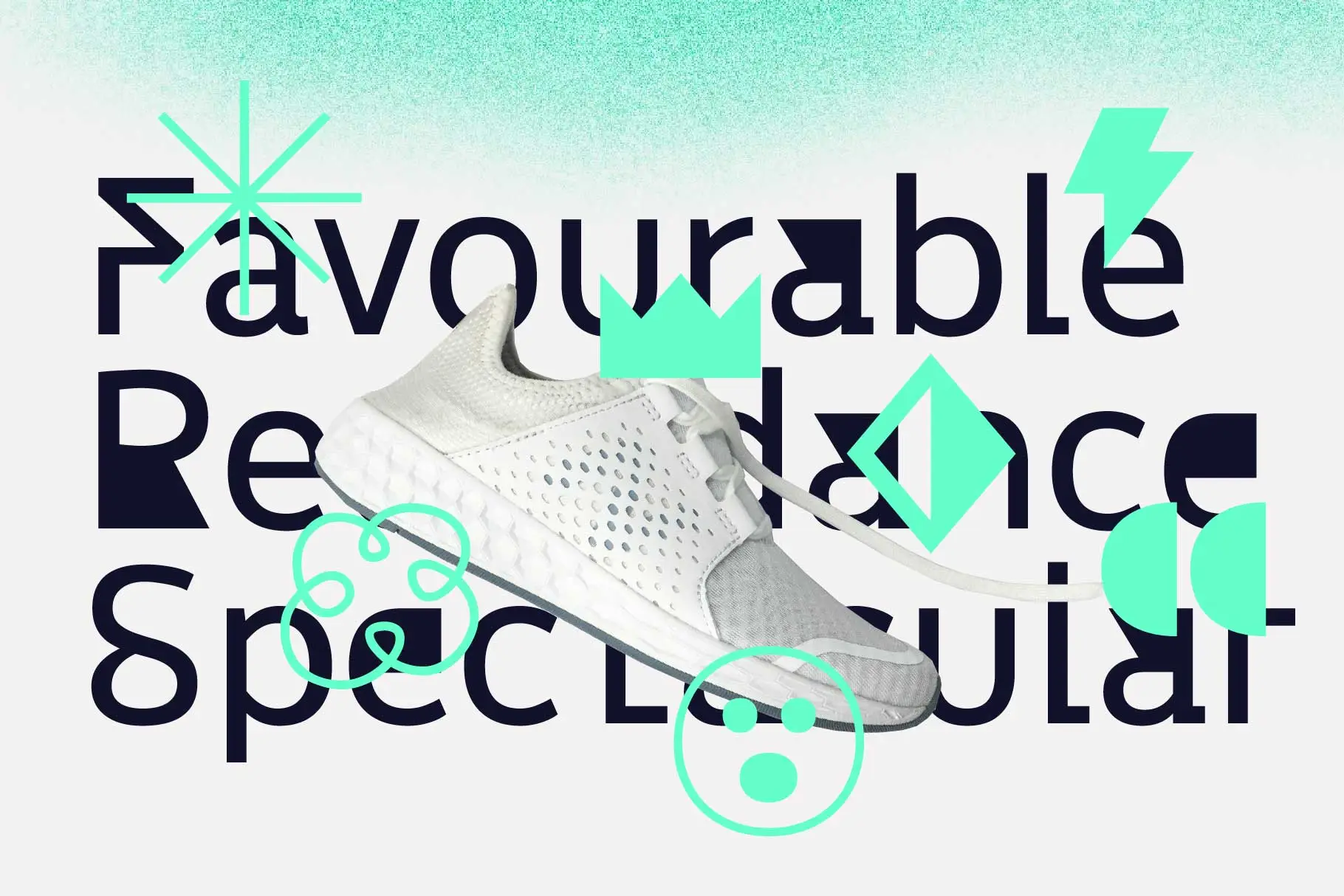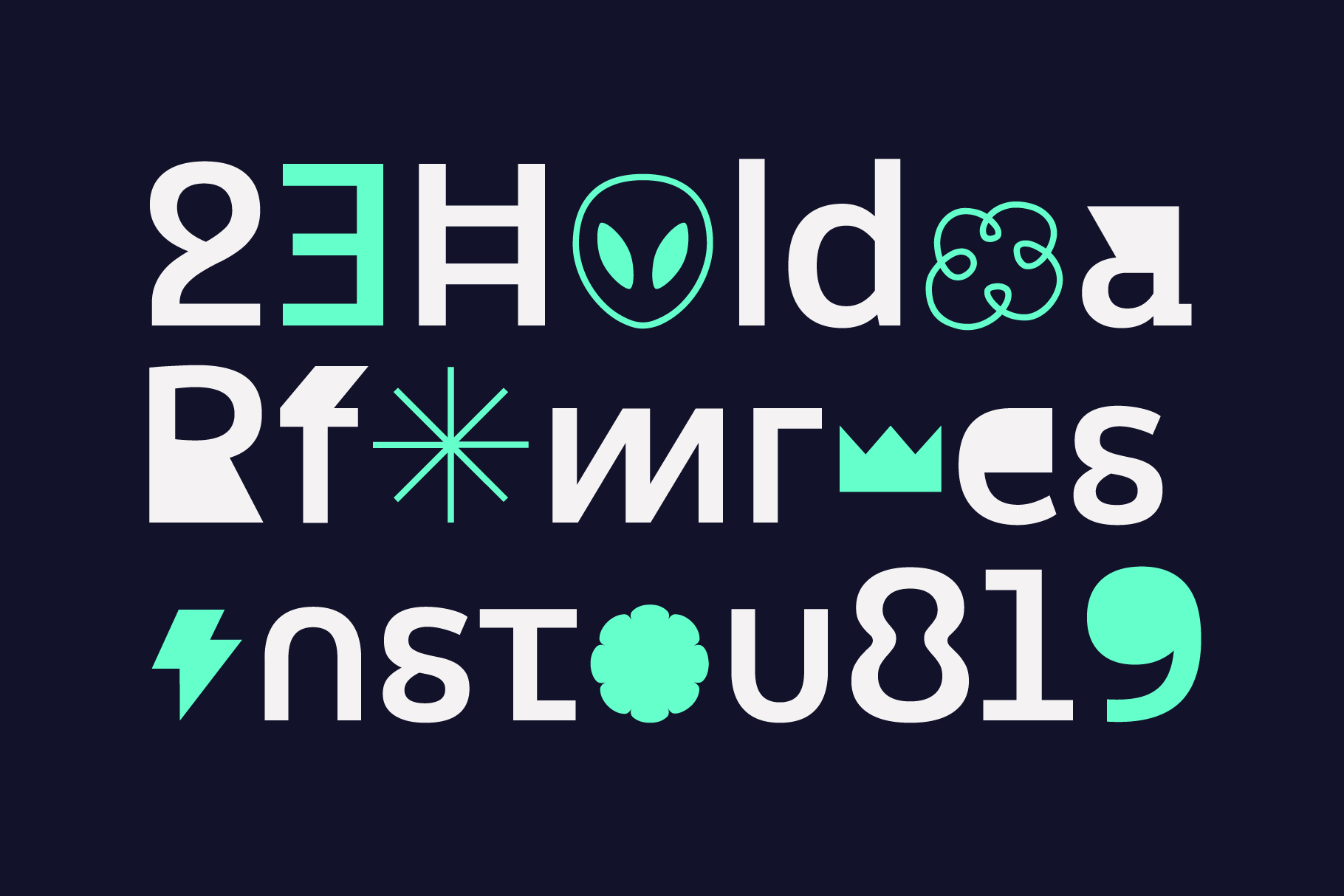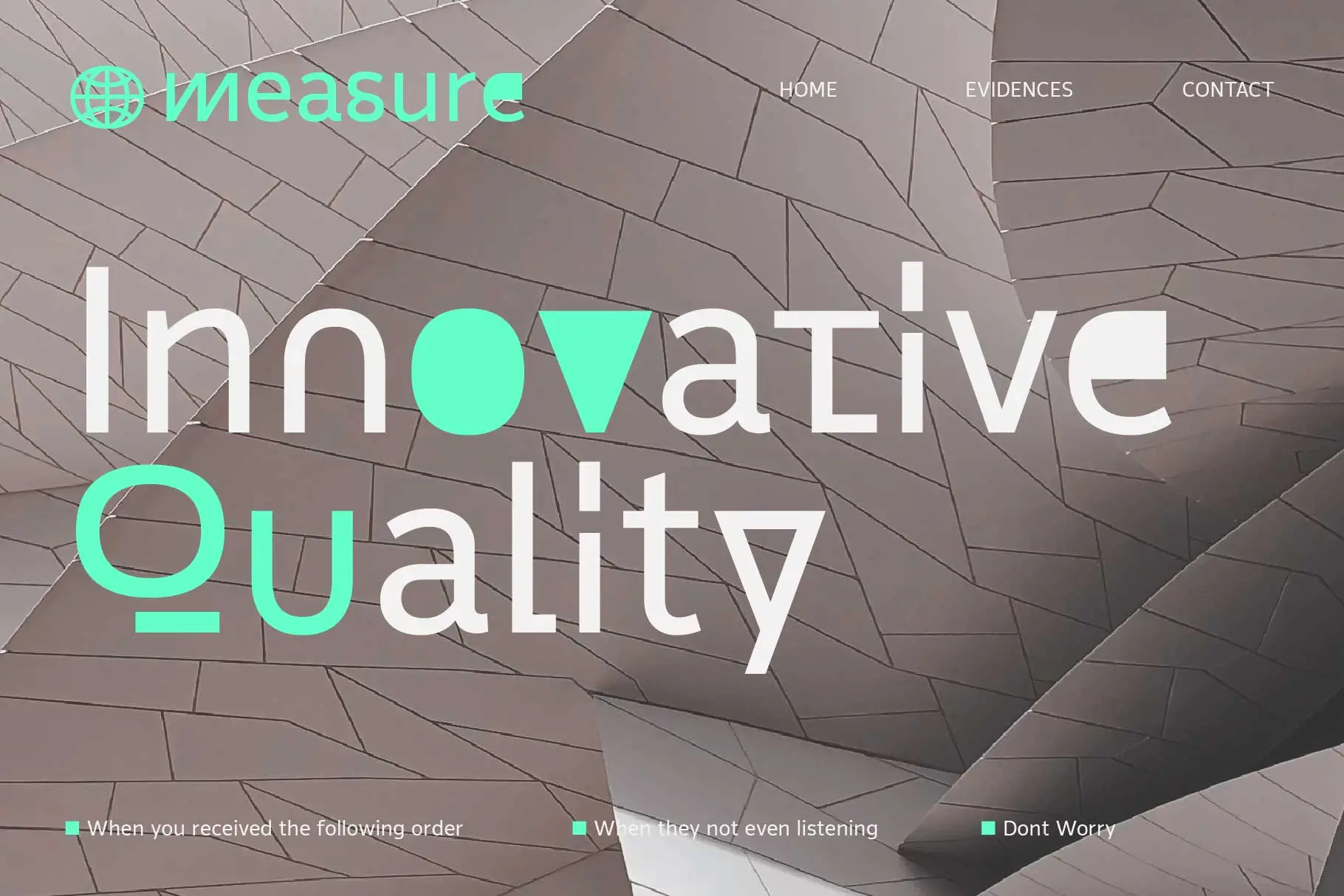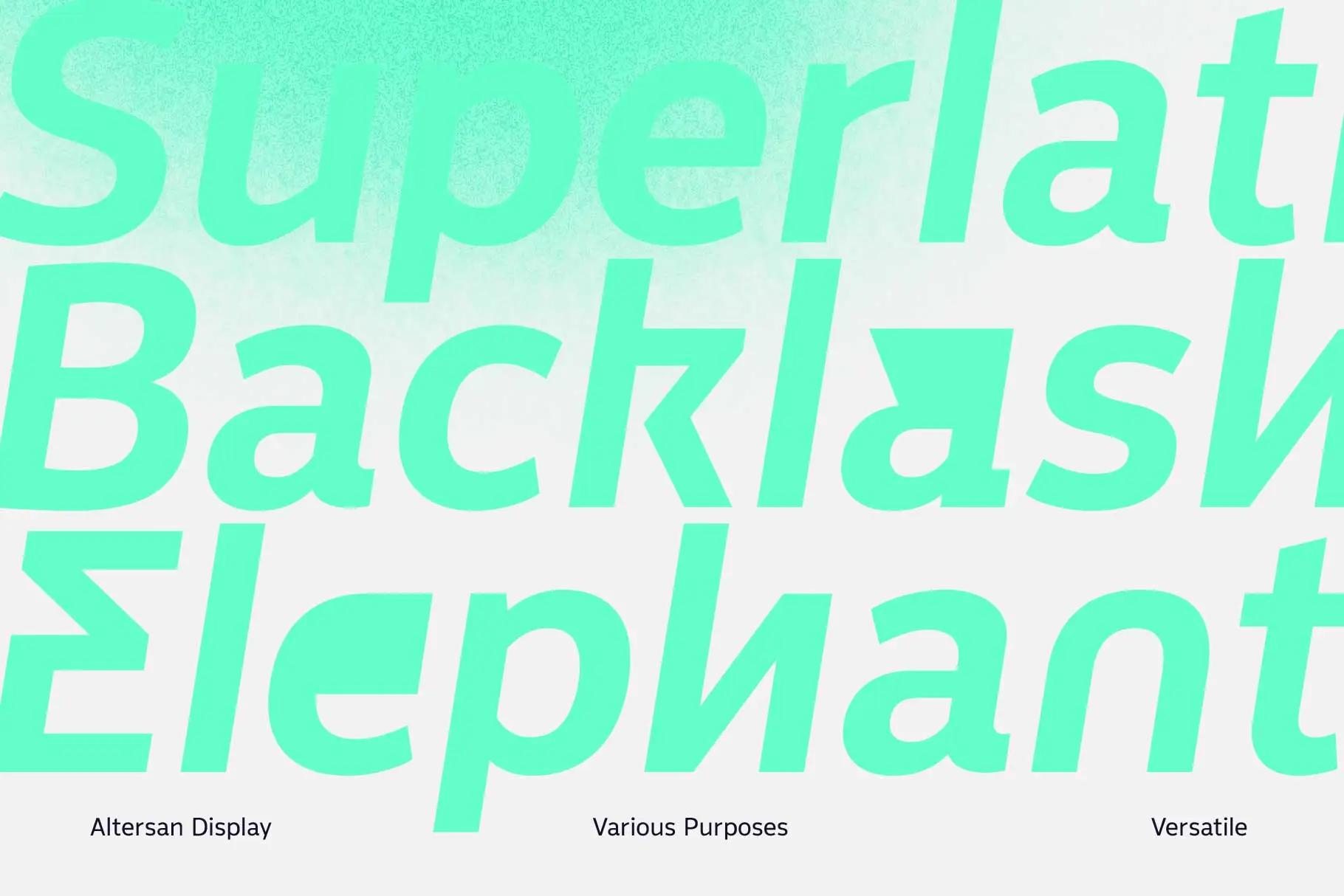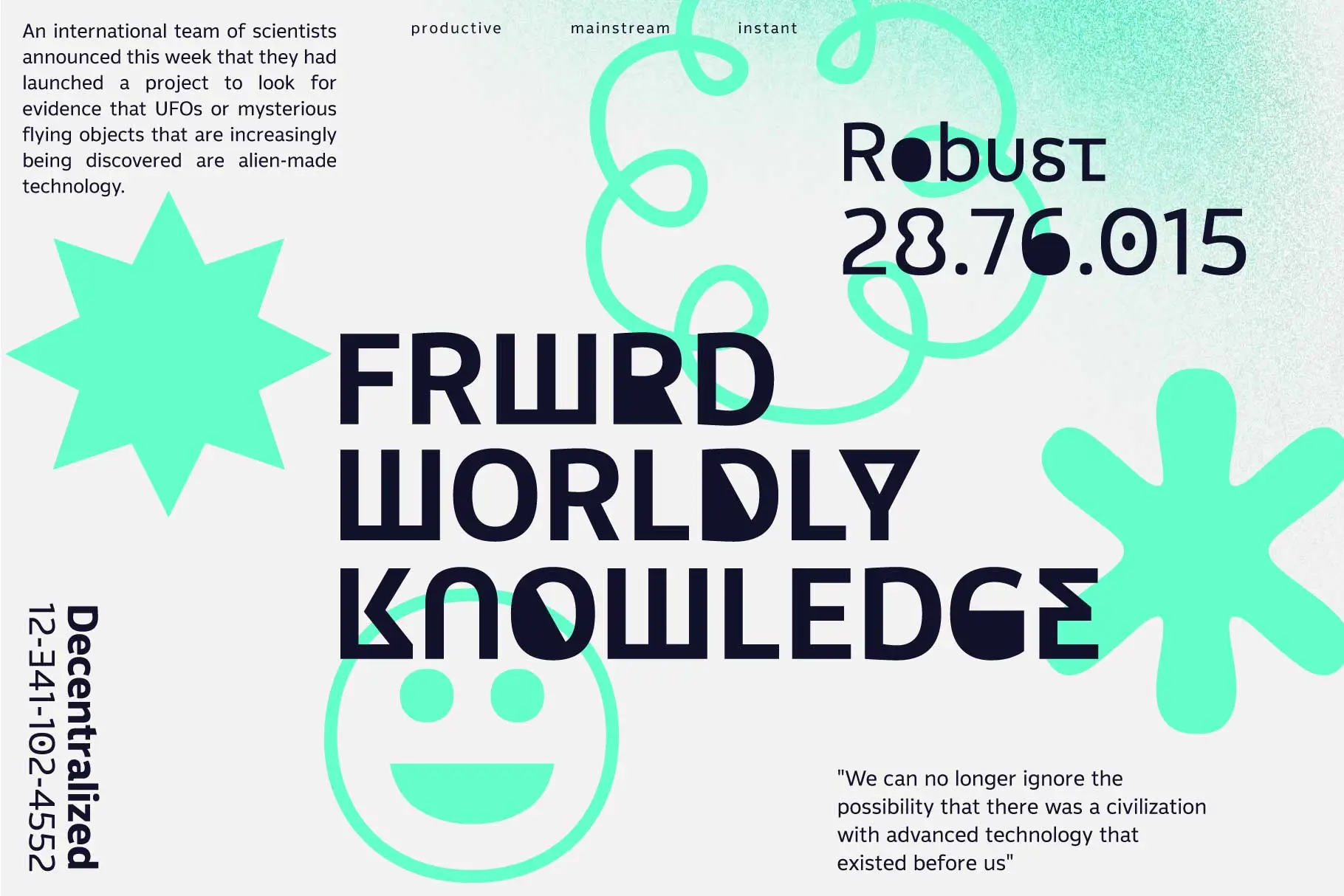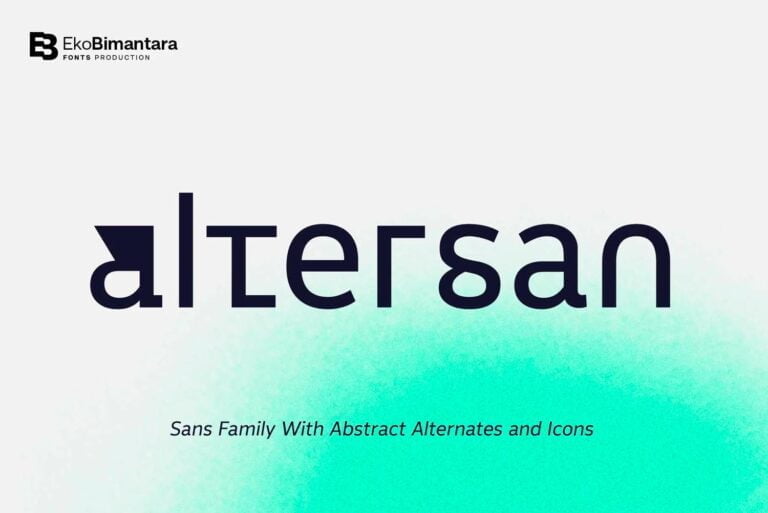
Altersan là bộ font sans serif nổi bật với cách tiếp cận độc đáo và mang tính khám phá trong thiết kế. Các hình tượng và biểu tượng thay thế trừu tượng của nó không giống bất kỳ biểu tượng nào khác, khiến nó trở thành sự lựa chọn tuyệt vời cho những ai muốn tạo ra những thiết kế mới mẻ và hiện đại.
Altersan bao gồm 8 kiểu từ Thin đến Black, mỗi kiểu đều có oblique phù hợp. Phạm vi trọng lượng và kiểu dáng này cho phép linh hoạt trong thiết kế. Ngoài ra, Altersan còn chứa 477 glyph hỗ trợ nhiều ngôn ngữ latinh, các ký tự tiêu chuẩn, dấu câu, ký hiệu và ký tự đặc biệt.
Một trong những tính năng độc đáo của Altersan là các glyph thay thế, có thể được truy cập thông qua kích hoạt tính năng opentype, stylistic alternates. Những hình tượng thay thế này mang tính trừu tượng đặc biệt, mang đến cho các nhà thiết kế nhiều khả năng sáng tạo.
Nhìn chung, Altersan là một bộ phông chữ hoàn hảo cho những ai muốn tạo ra những thiết kế hiện đại và phá cách. Nó lý tưởng cho các dự án xây dựng thương hiệu, quảng cáo và thiết kế kỹ thuật số, cùng nhiều các lĩnh vực thiết kế khác.